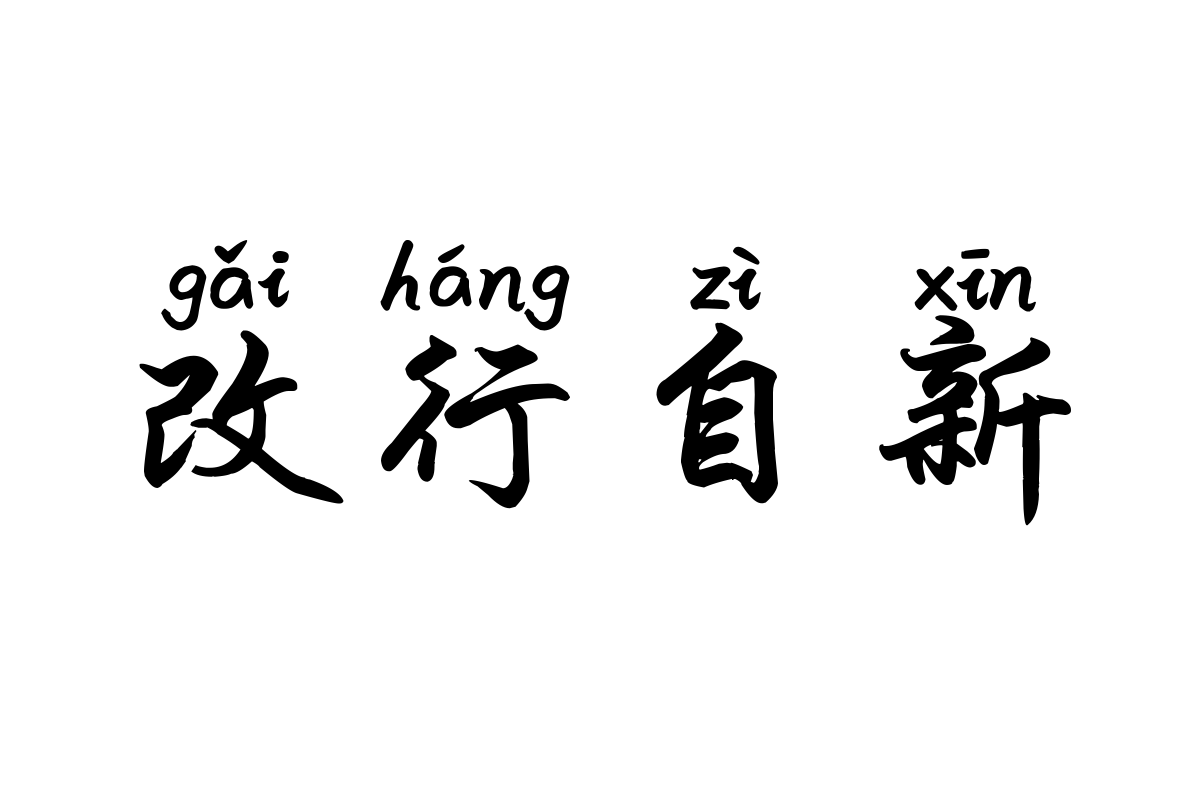
米开软笔行楷拼音体是一款由米开设计公司开发的字体,它结合了软笔书法的流畅性与行楷的简洁性,创造出一种独特的字体风格。这款字体具有以下特点:
1. 字形结构:米开软笔行楷拼音体采用了传统的汉字结构,每个字都保持了一定的平衡和对称性。同时,它也保留了一些现代感,使得字体更加符合现代人的审美需求。
2. 笔画处理:在笔画的处理上,米开软笔行楷拼音体注重线条的流畅性和力度,使得每个字都显得生动有力。同时,它也保留了一些传统书法的特点,如笔画的粗细变化和顿挫感。
3. 字体风格:米开软笔行楷拼音体的字体风格独特,既有现代感又不失传统韵味。它适合用于各种场合,如书籍、杂志、广告等,能够吸引人们的注意力。
4. 适用范围:米开软笔行楷拼音体适用于多种场景,如网站、APP、海报、宣传册等。它不仅能够提升文字的视觉效果,还能够增强信息的传达效果。
总之,米开软笔行楷拼音体是一款集传统与现代于一身的字体,它既保留了汉字的基本元素,又融入了现代设计的理念,为设计师提供了更多的创作空间。
米开软笔行楷拼音体